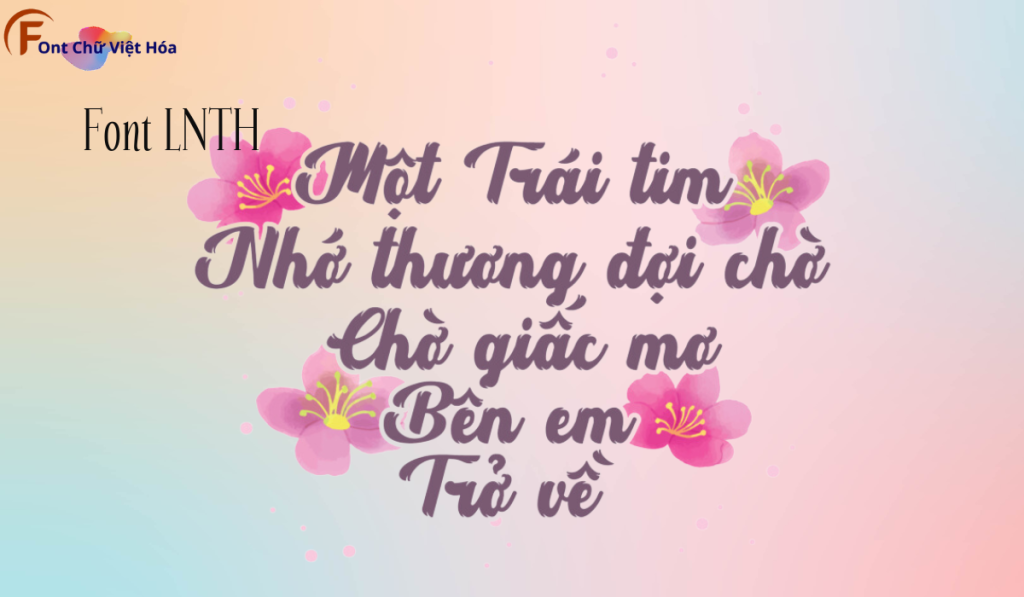
Font LNTH Headbrush Việt Hóa
Tác giả: LNTH
Phân loại: Cá tính, độc đáo
Kiểu chữ: Kiểu chữ thư pháp
Font LNTH Headbrush Việt Hóa là một font chữ viết tay, thuộc bộ LNTH, với thiết kế tự nhiên và thân thiện. Phong cách của font này phù hợp với các dự án thiết kế cần sự gần gũi và ấm áp, như thiệp mời, bìa sách, hoặc bảng hiệu. Font LNTH Headbrush Việt Hóa mang đến sự tự nhiên và dễ nhận diện, ứng dụng trong các lĩnh vực sáng tạo. Đặc điểm hình dạng của font bao gồm các nét bút lông mềm mại và tự nhiên, giúp tăng tính thẩm mỹ và sự chú ý. Việc Việt hóa font giúp người dùng dễ dàng sử dụng trong các thiết kế tiếng Việt, mang lại sự tiện lợi và linh hoạt.